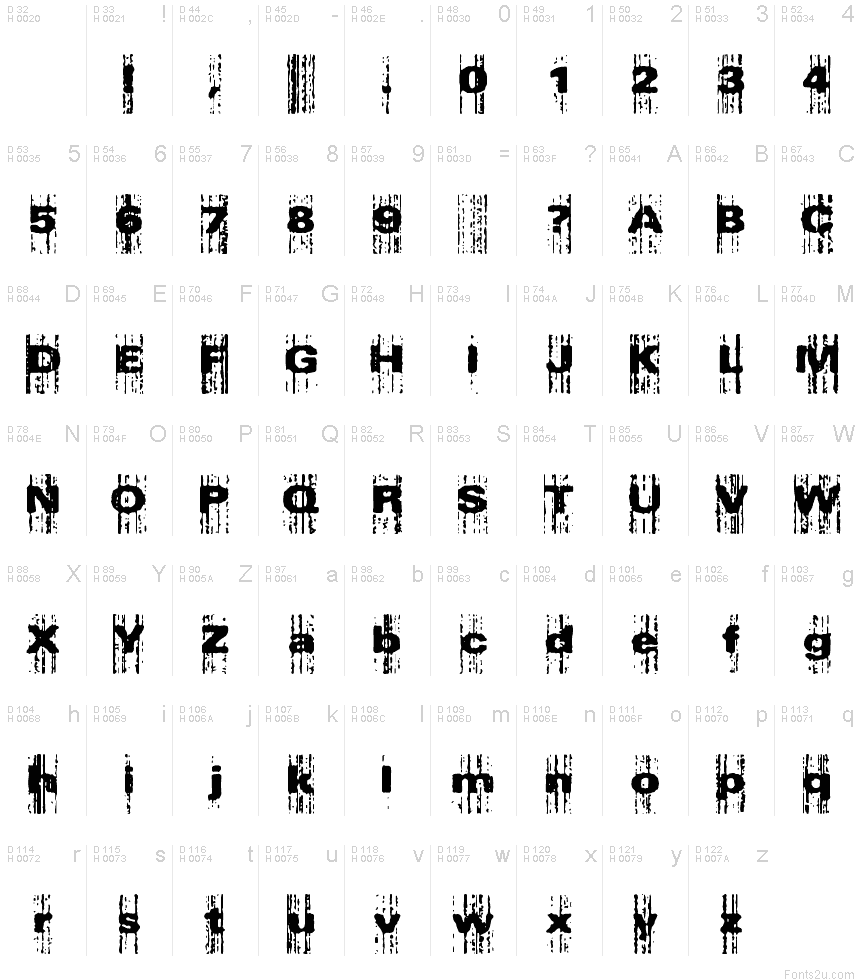
Xerox Malfunction od AEnigma Fonts to bezpłatny, zniekształcony font displayowy o brudnym, glitchowym charakterze przypominającym zaciętą kserokopiarkę. Litery wyglądają na zapchane, rozmazane i częściowo wyjedzone, z zaciekami, kropkami i poszarpanymi krawędziami, które powtarzają się w całym zestawie, nadając krojowi wygląd błędu maszyny zamienionego w typografię.
Pasuje do plakatów, okładek zinów, ulotek zespołów, horrorowych nagłówków i undergroundowych znaków, gdzie czyste wykończenie mijałoby się z celem. Jako darmowy font, sprawdza się również w krótkich nagłówkach, inicjałach i surowych monogramach, ponieważ ciężkie plamy i smużąca tekstura sprawiają, że nawet kilka liter wygląda jak uszkodzony wydruk.